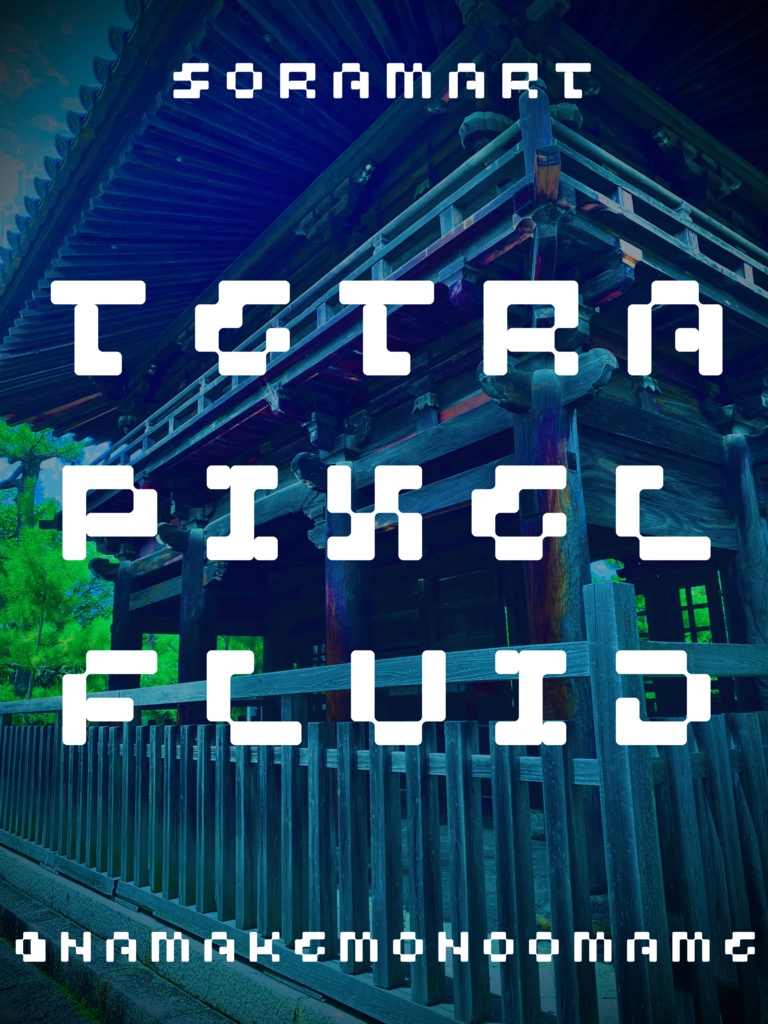
そらマートフォントデータ”Tetra Pixel Fluid”Digital2,500 JPY加入购物车Buy a GiftAbout Gift最低限のドット数で文字を表現することをめざしたフォント…のカドを丸くアレンジした "Tetra Pixel Fluid" です。 「TrueTypeフォントファイル」という形式です。 ダウンロードした後、Zipファイル内のデータをインストールしてお使いください。 このフォントは商用利用可となっております。 お客様の制作・創作活動のお役に立てれば幸いです。 ※使用上の注意事項などは、添付のReadmeをお読みください。そらマートVisit FANBOX!Fontsフォントデータ”Abyss Dive Punk Retro”そらマート2,500 JPYFontsフォントデータ”Abyss Dive Punk Wide”そらマート0 JPYFontsフォントデータ”Abyss Dive Punk”そらマート0 JPYFontsフォントデータ”Emerald Sphere Sprite”そらマート2,500 JPYFontsフォントデータ”Emerald Sphere Long”そらマート2,500 JPYFontsフォントデータ”Emerald Sphere”そらマート2,500 JPYFontsフォントデータ”Monolith Glitch”そらマート2,500 JPYFontsフォントデータ”Monolith Formula”そらマート2,500 JPYFontsフォントデータ”Rolling Cute”そらマート2,500 JPYFontsフォントデータ”Tricky Wire Merge”そらマート2,500 JPYFontsフォントデータ”Tricky Layer Wide”そらマート2,500 JPYFontsフォントデータ”Tricky Layer”そらマート2,500 JPYFontsフォントデータ”Popcorn Tab Plasma”そらマート2,500 JPYFontsフォントデータ”Popcorn Tab Heavy”そらマート2,500 JPYFontsフォントデータ”Popcorn Tab”そらマート2,500 JPYFontsフォントデータ”Tetra Pixel Dash”そらマート2,500 JPYFontsフォントデータ”Tetra Pixel”そらマート2,500 JPYFontsフォントデータ”Neon-Lit Empire Long”そらマート2,500 JPYFontsフォントデータ”Neon-Lit Empire”そらマート2,500 JPYFontsフォントデータ”Jumping Meteor Drop”そらマート2,500 JPY查看更多